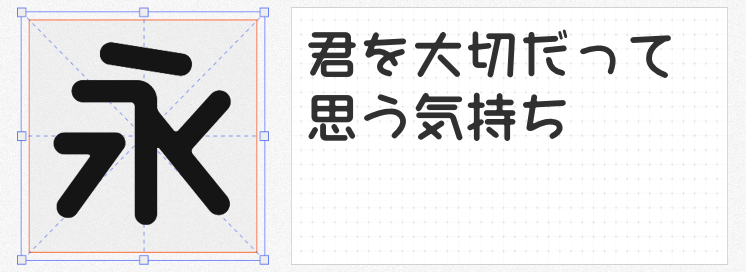
在设计中,日系字体以其独特的可爱风格与创意设计,成为营造温暖氛围、传递年轻活力的利器。本文精选四款免费商用且风格各异的日系字体,为设计师提供创意灵感与实用选择。
这款字体以日文名「にゃしぃフレンズ」命名,字如其名,每个字符都镶嵌着小巧的心形装饰,仿佛猫咪爪印般俏皮。其手写风格自然流畅,笔画粗细变化柔和,充满童趣与亲和力。适用于儿童绘本、手账模板或节日贺卡设计,轻松传递温暖与甜蜜。
尤穆尔 Normal 以“中年男子变身美少女”的奇妙设定为灵感,笔画圆润且结构左右倾斜,打破传统字体的平衡感,带来意外萌趣。其设计融合实验性与兼容性,部分汉字可转换为简体,适合需要独特视觉冲击力的场景,如动漫周边、游戏界面或创意海报,为作品注入反差萌的戏剧张力。
该字体模拟荧光笔书写效果,笔画粗犷中透出荧光色系的活力,POP 氛围浓厚。其包含6900余字符,覆盖常用汉字与日文假名,适合制作手账素材、店铺招牌或社交媒体封面。使用时需注意保留版权信息,但无需额外授权,是低成本打造年轻化设计的理想选择。
这款字体以纯手写方式呈现,笔画轻盈如少女日记中的字迹,适合用于信件、姓名贴纸或女性向产品包装。其柔和的视觉效果能瞬间软化画面氛围,让设计充满私密感与故事性。无论是电子邀请函还是实体明信片,都能通过它传递细腻情感。